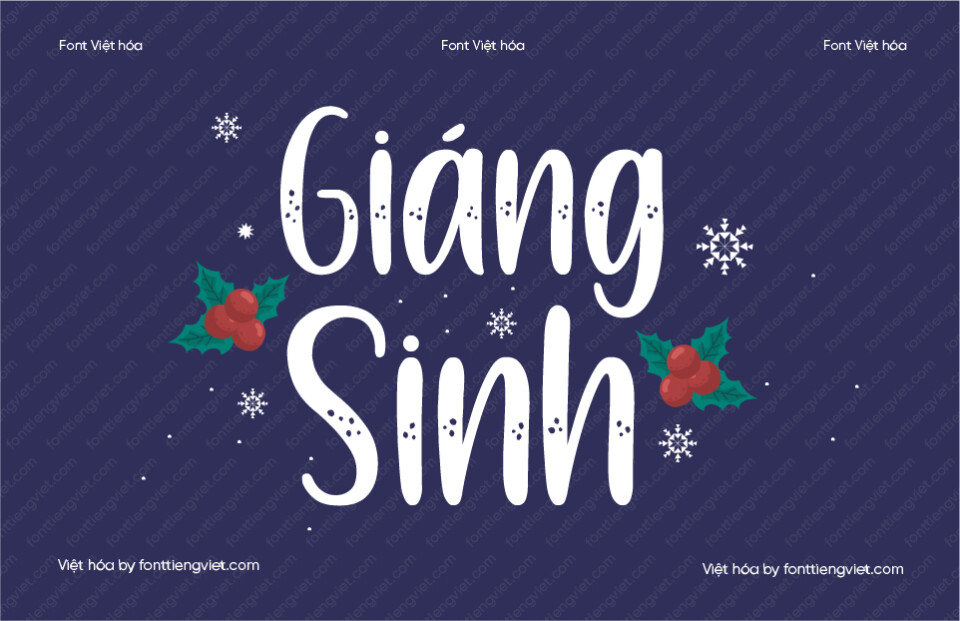
Font Việt hóa 1FTV VIP Snowy Christmas
Trong thế giới thiết kế đồ họa hiện đại việc lựa chọn bộ Font Miễn Phí chất lượng luôn là ưu tiên hàng đầu của các bạn học sinh và giáo viên. Đặc biệt khi mùa đông và các dịp lễ cuối năm đang đến gần bộ Font Việt hóa 1FTV VIP Snowy Christmas trở thành một công cụ không thể thiếu để tạo nên những sản phẩm truyền thông ấn tượng. Với phong cách mềm mại uyển chuyển và mang đậm hơi thở của những bông tuyết trắng tinh khôi bộ font này giúp các bài thuyết trình hay thiệp chúc mừng trở nên sinh động và ấm áp hơn bao giờ hết. Việc tìm kiếm và sử dụng các font chữ đã được việt hóa chuẩn giúp người dùng không còn lo lắng về lỗi hiển thị dấu tiếng Việt một vấn đề thường gặp đối với các bộ font quốc tế chưa qua chỉnh sửa.
Đặc điểm nổi bật của bộ Font Việt hóa 1FTV VIP Snowy Christmas
Bộ Font Việt hóa 1FTV VIP Snowy Christmas được thiết kế dựa trên cảm hứng từ những ngày lễ Giáng sinh rực rỡ và tràn đầy niềm vui. Từng nét chữ trong bộ font này đều gợi lên hình ảnh của sự sum vầy niềm hạnh phúc và vẻ đẹp của thiên nhiên mùa đông lạnh giá nhưng đầy cảm xúc. Đây là lựa chọn hoàn hảo cho các dự án thiết kế thiệp mời băng rôn quảng cáo hoặc trang trí báo tường tại trường học.
Khả năng hiển thị tiếng Việt hoàn hảo
Điểm mạnh nhất của Font Việt hóa 1FTV VIP Snowy Christmas chính là sự tương thích tuyệt vời với bảng mã Unicode. Các dấu thanh được tinh chỉnh tỉ mỉ giúp tổng thể văn bản trông cân đối và hài hòa. Điều này cực kỳ quan trọng đối với các em học sinh khi thực hiện các dự án học tập đòi hỏi tính thẩm mỹ cao và sự chuyên nghiệp trong cách trình bày nội dung văn bản tiếng Việt.
Phong cách thiết kế sang trọng và ấm cúng
Với các đường nét uốn lượn nghệ thuật bộ font mang lại cảm giác sang trọng nhưng vẫn rất gần gũi. Nó không chỉ đơn thuần là một bộ chữ cái mà còn là một tác phẩm nghệ thuật giúp truyền tải thông điệp yêu thương một cách trọn vẹn nhất. Khi kết hợp với các tông màu như đỏ xanh lá hay vàng kim bộ font sẽ làm nổi bật lên chủ đề lễ hội mà bạn đang hướng tới.
Ứng dụng thực tế của Font Việt hóa 1FTV VIP Snowy Christmas trong học tập
Đối với môi trường giáo dục việc sử dụng Font Việt hóa 1FTV VIP Snowy Christmas mang lại luồng gió mới cho các hoạt động sáng tạo. Giáo viên có thể dùng font chữ này để thiết kế các phiếu bài tập thú vị hoặc các bảng tin lớp học nhằm thu hút sự chú ý của học sinh. Các em học sinh cũng có thể tự tay làm những tấm thiệp điện tử gửi tặng thầy cô và bạn bè nhân dịp Noel.
Tạo bài giảng PowerPoint sinh động
Sử dụng bộ font này trong các slide mở đầu hoặc tiêu đề chương sẽ giúp bài giảng trở nên cuốn hút hơn. Sự độc đáo của các ký tự sẽ khơi gợi trí tưởng tượng và niềm yêu thích sáng tạo trong mỗi cá nhân giúp tiết học không còn khô khan.
Thiết kế sản phẩm lưu niệm lớp học
Ngoài ra bộ font còn rất phù hợp để in ấn trên các sản phẩm quà tặng như cốc sứ áo thun hoặc sổ tay kỷ niệm. Tính ứng dụng cao và sự đa dạng trong cách thể hiện khiến nó luôn nằm trong danh sách những bộ font được săn đón nhiều nhất mỗi dịp cuối năm.